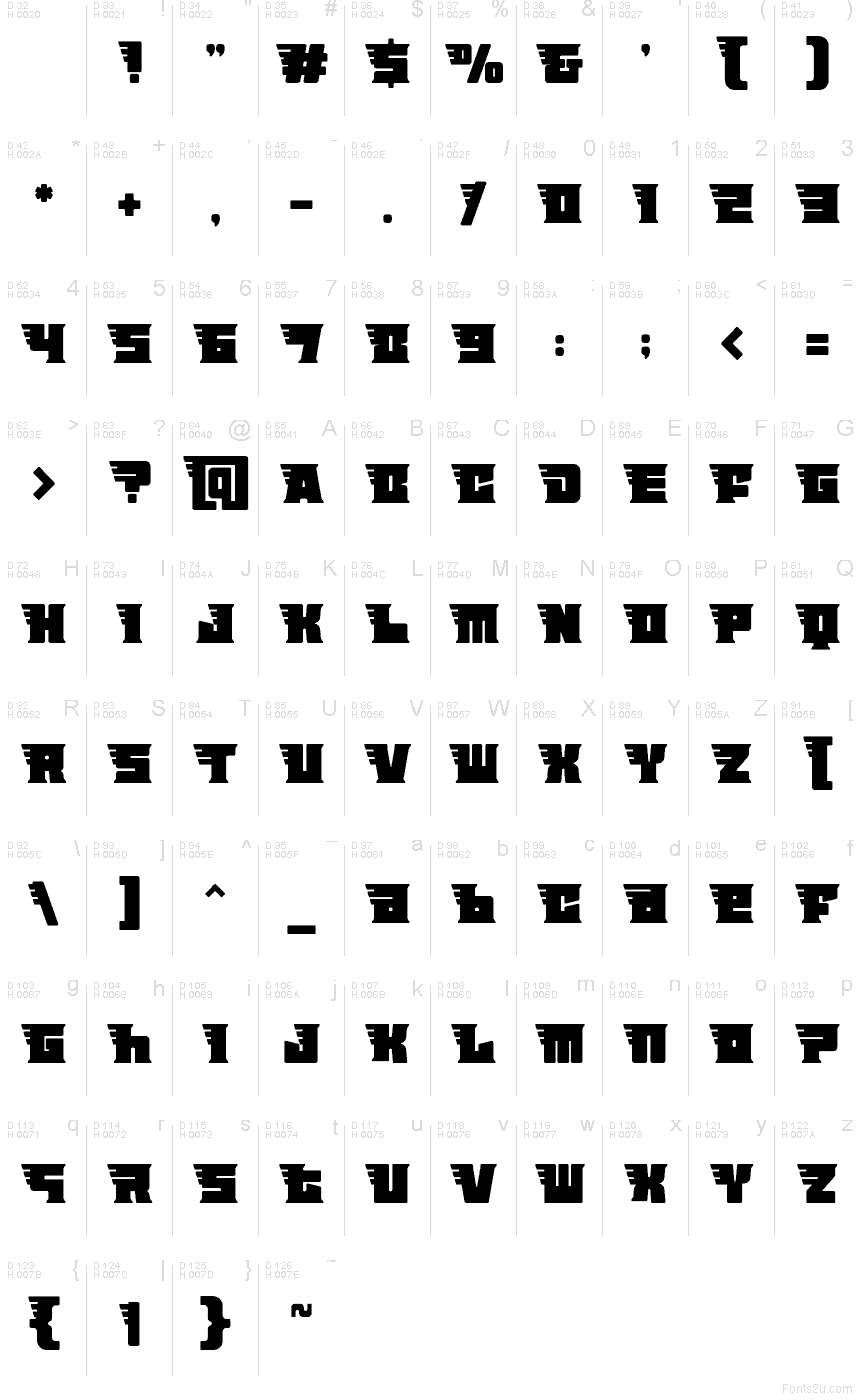
Astral Zenith Eleven od Putracetol Studio je bezplatné sci-fi písmo, které definují masivní blokové tvary s opakovanými vodorovnými řezy připomínajícími skenovací linky nebo technické značky. Tento rytmický prvek dodává znakům napětí a dynamiku, díky čemuž design působí spíše jako součást kosmické technologie než jako generický dekorativní styl.
Nejlépe vynikne v názvech her, e-sportových grafikách, nadpisech plakátů, obalech alb či streamovacích překryvech, kde krátké texty potřebují ostrý elektronický nádech. Detaily řezů dodávají logům, názvům frakcí i úvodním obrazovkám potřebnou ostrost, zejména pokud hledáte kompaktní nápis odkazující na stroje a ovládací panely.
Astral Zenith Eleven